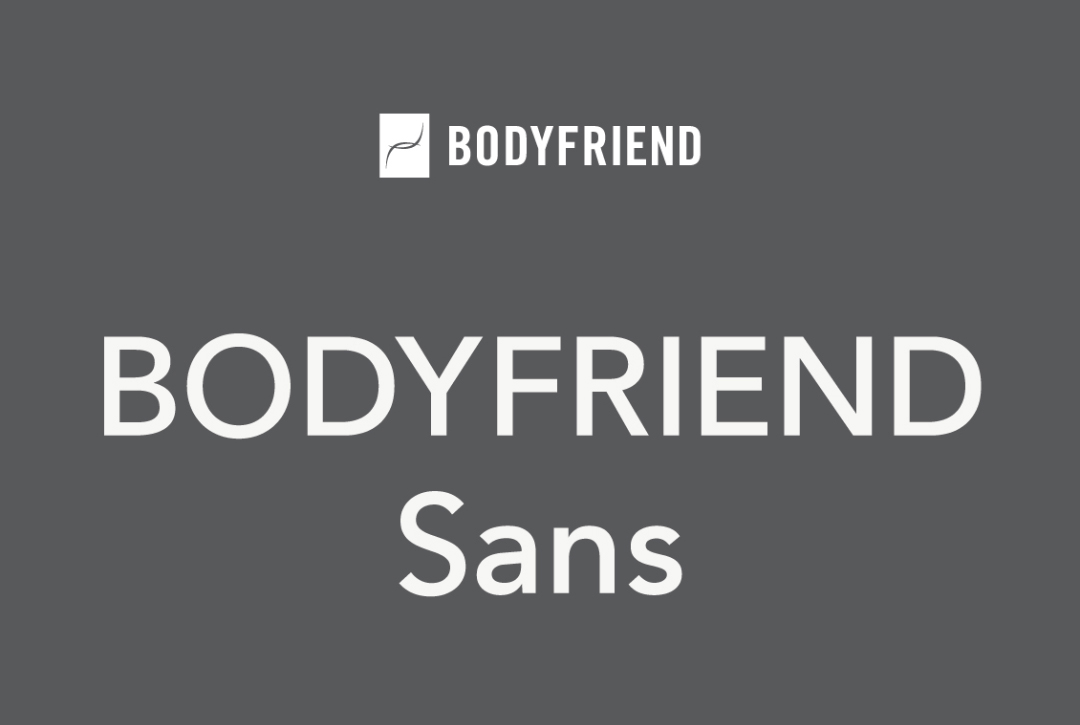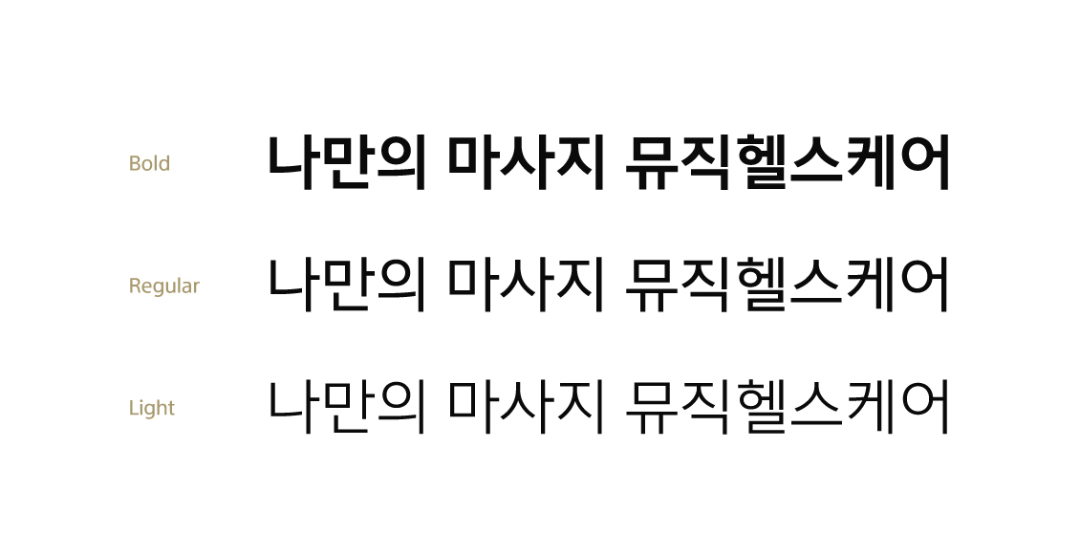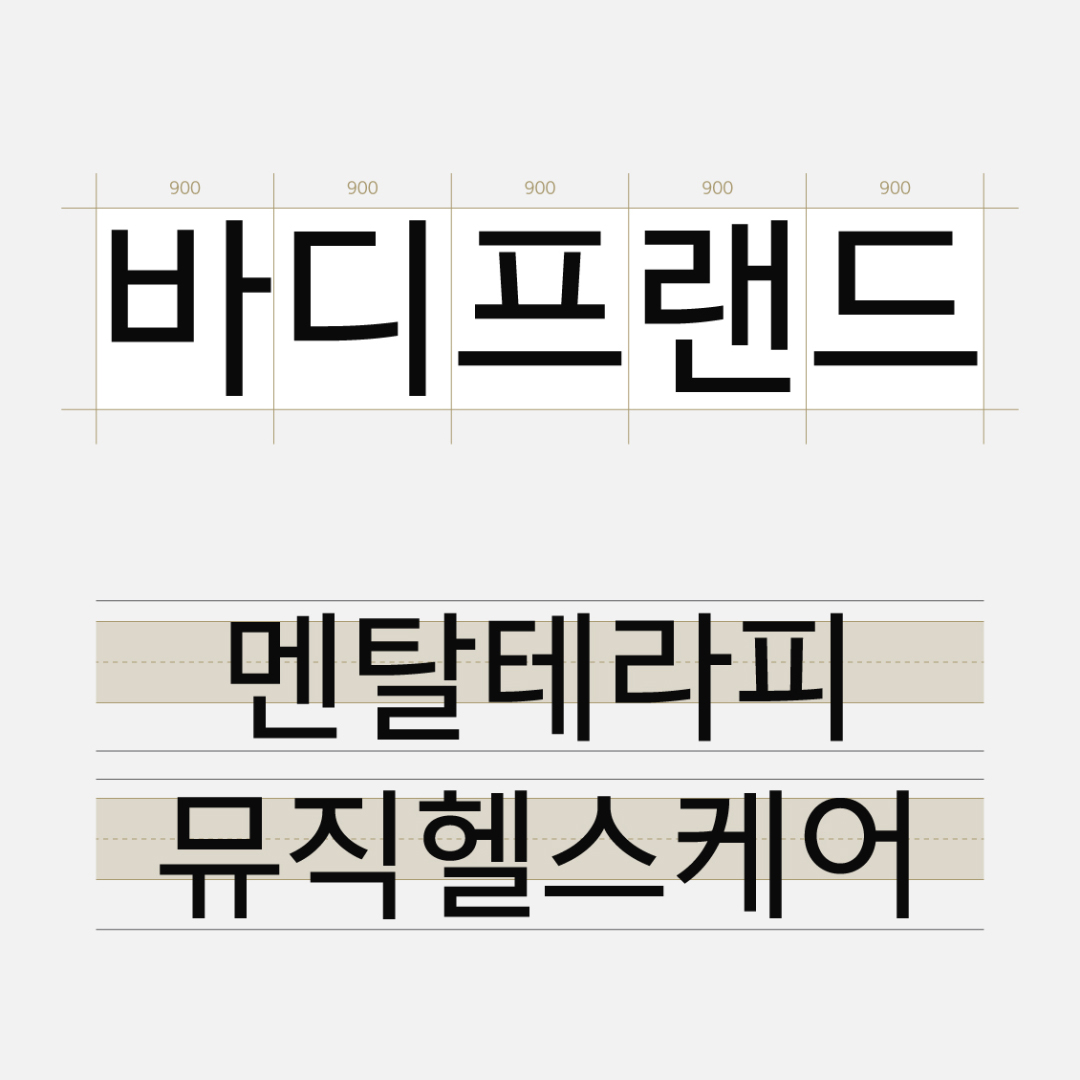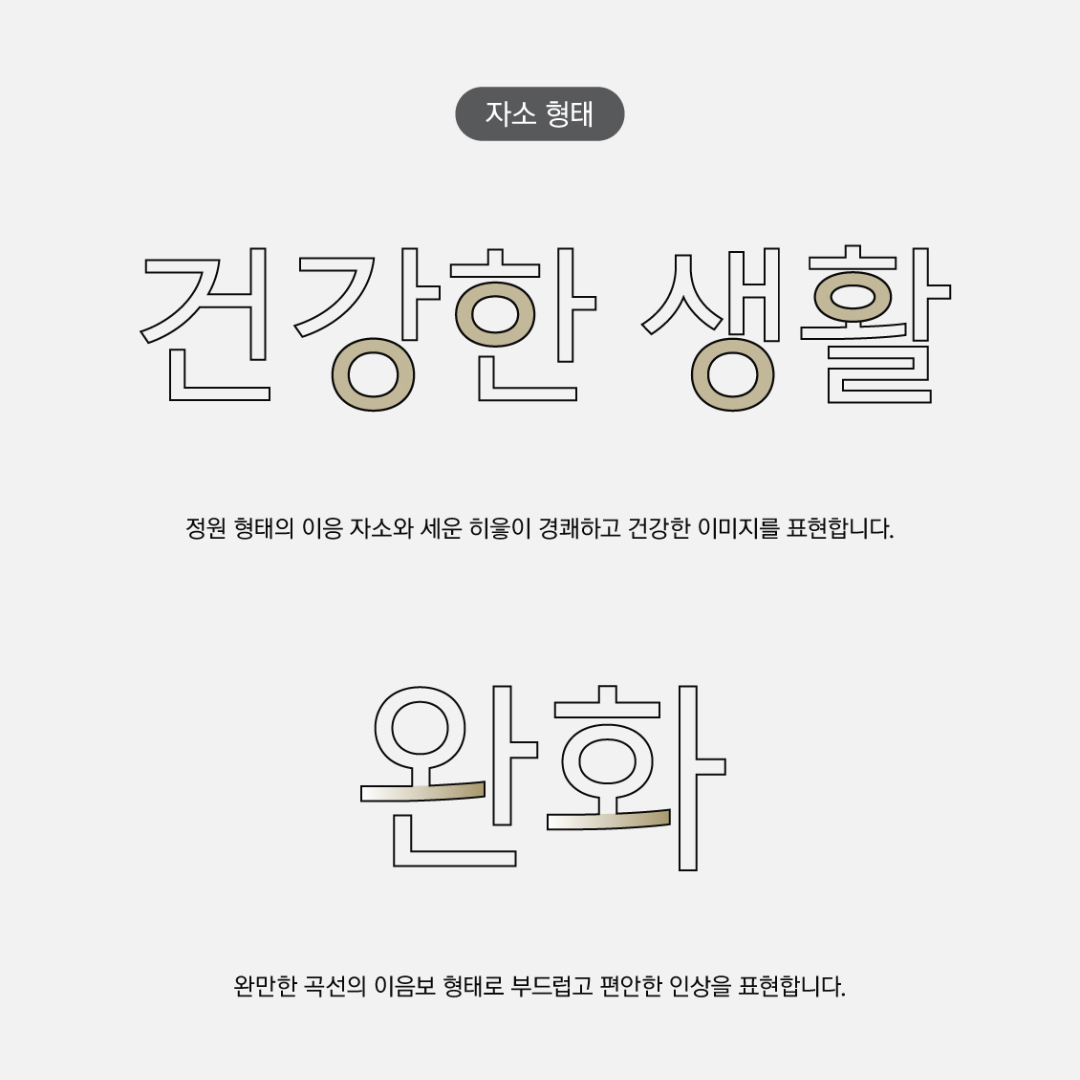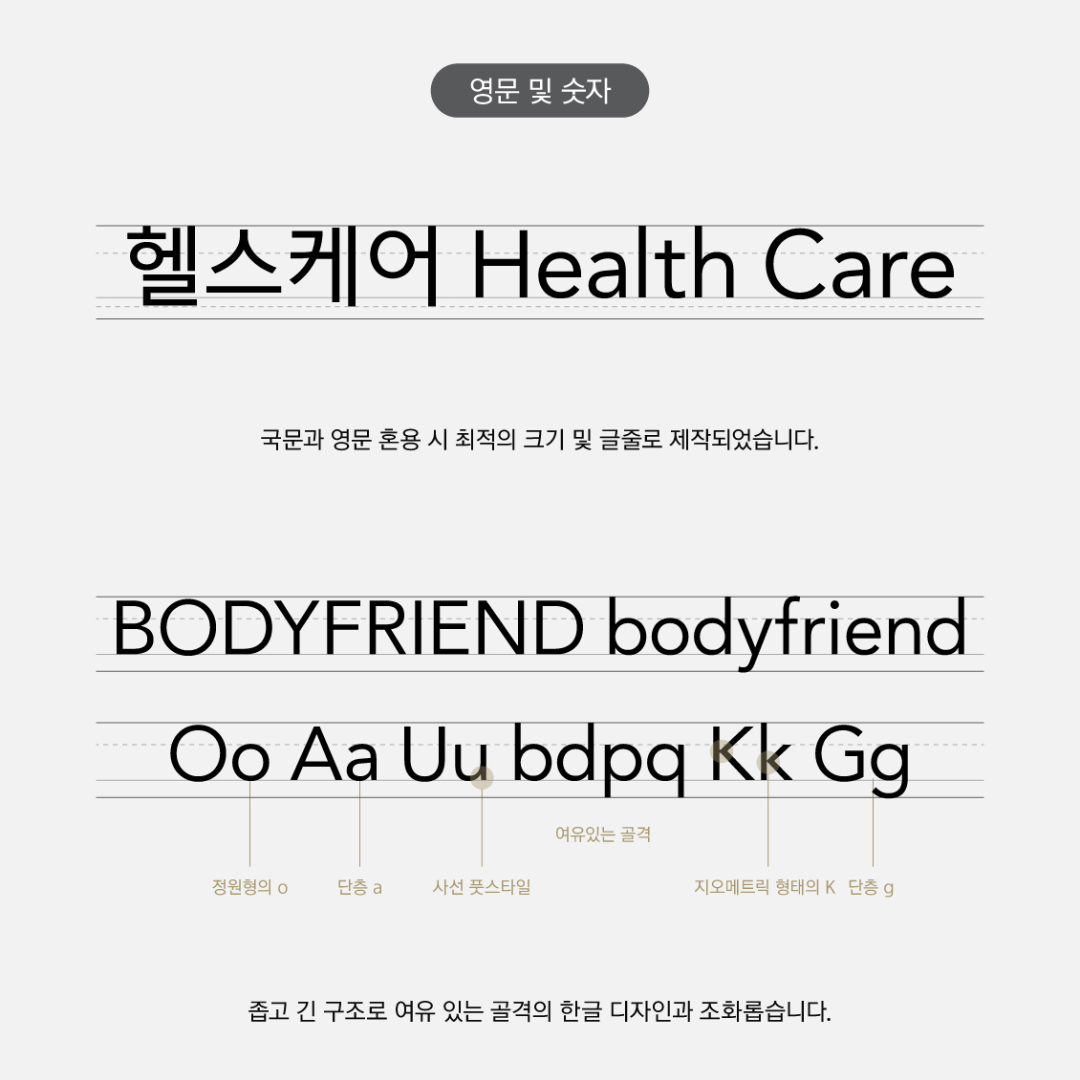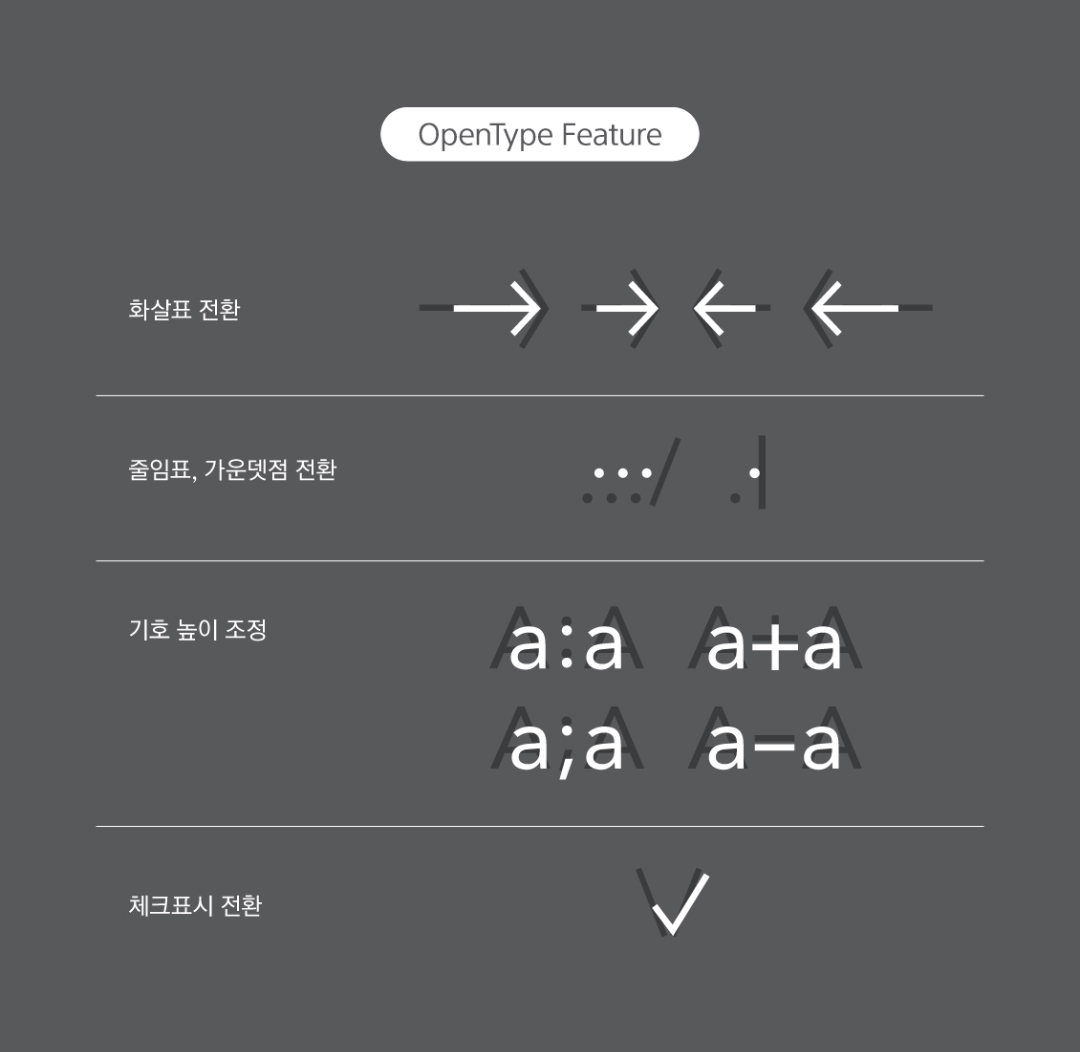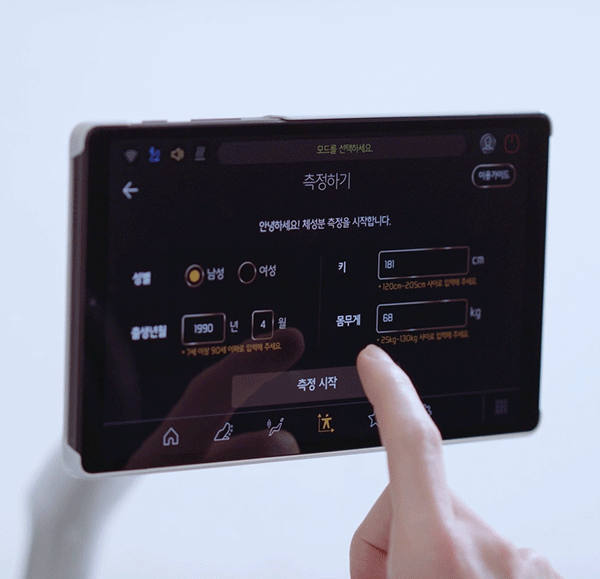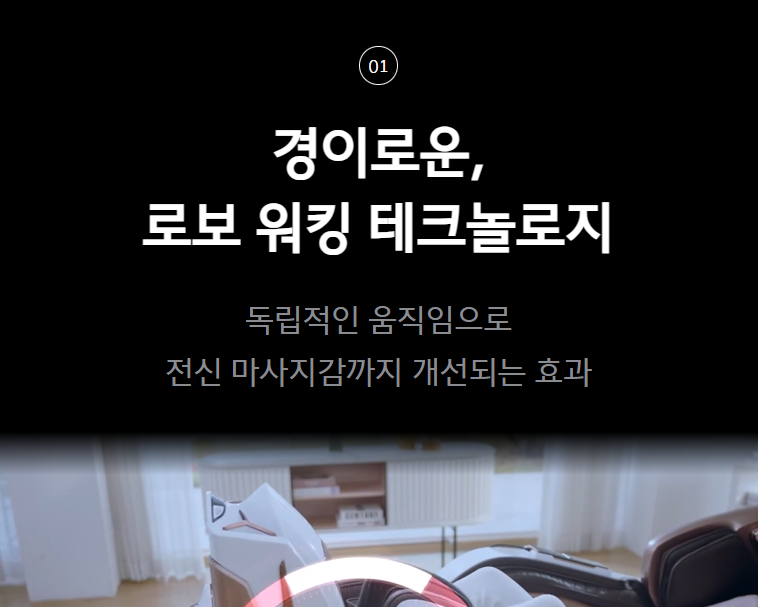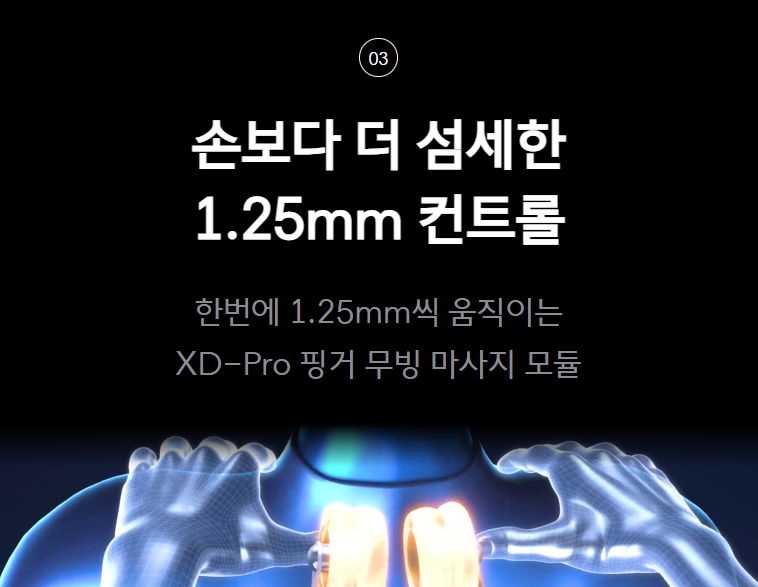
오늘 알아볼 서체는 홈헬스케어 브랜드인 바디프랜드의 UI 전용 서체로 제작한 「BODYFRIEND Sans」입니다. '안마의자'하면 딱 떠오르는 브랜드가 아닐까 싶은데요~ 바디프랜드의 다양한 헬스케어 의료기기들에 들어가는 리모컨 디스플레이 환경에 최적화한 서체를 개발하게 되었습니다. UI에 중요한 가독성을 중점적으로 하여 디자인까지 고려한 바디프랜드 산스를 소개해 드려요.
UI에 최적화한 서체
전용서체를 제작할 때 가장 중요한 부분 중 하나는 '어디에, 어떻게 사용될 서체인가' 입니다. 기존 바디프랜드 UI 서체를 분석해 보니 다양한 디스플레이 환경에 적합하지 않은 굵기를 갖고 있었습니다. 저희는 3가지 굵기로 구분하여 고해상도와 저해상도 디바이스 모두를 아우를 수 있는 서체를 제안드렸습니다.
굵기를 정한 후 이를 토대로 적절한 골격과 글줄을 설정하였습니다. 일정한 고정 자폭에 상단에 위치한 글줄, 골격은 여유 있게 디자인하여 명료하면서도 활기찬 분위기를 느낄 수 있습니다.
건강하고 경쾌한 이미지
바디프랜드의 기존 전용서체는 획에 굴림이 확연히 더 많은 스타일이었지만, 굴림 정도에 클수록 화면상에서 굴곡 현상을 일으켜 가독성을 방해할 수 있습니다.
이를 개선하여 부드러운 인상을 줄 수 있는 정도의 하단부 쪽 곡선과 정원형의 이응꼴 형태는 유지하고, 대부분의 굴림을 삭제해 훨씬 깔끔하고 경쾌한 인상을 주었습니다.
영문 및 숫자에도 동일한 특징을 적용하여 국문과의 혼용 시 조화롭도록 디자인했습니다. 영문 외에도 프랑스어, 이탈리어어도 함께 개발해 활용도를 높였습니다.
또한 편리한 사용을 고려하여 오픈타입(OpenType) 기능을 추가했습니다. 해당 문자를 타이핑하면 자동으로 형태가 전환되거나 높이가 조정됩니다.
*OpenType 기능을 지원하는 프로그램에서만 적용됨
바디프랜드 산스의 활용
바디프랜드 안마기기에 포함된 디스플레이 화면에 적용된 모습을 볼 수 있습니다. 세 가지 굵기로 제작했기 때문에 다양한 환경에서 적절하게 사용할 수 있습니다.
리모컨 UI 뿐 아니라 홈페이지 내 상품 상세 페이지 등에도 활용된 모습을 볼 수 있습니다. 텍스트가 깔끔하고 시원한 느낌을 주어 글씨와 내용이 눈에 잘 들어옵니다.